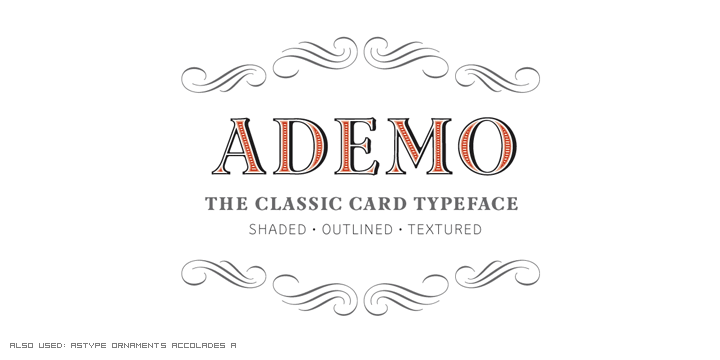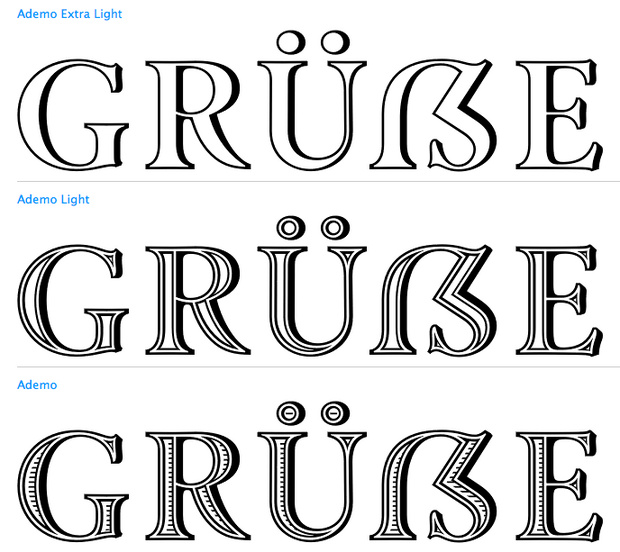
Ademo is a classic, shaded and perspective looking display font. The design is based on two typefaces designed by Carl Albert Fahrenwaldt and published between 1931– 1932 by the German Schriftguss AG type foundry.
Ademos special Fill fonts can be used for building multi colored text or for special finishing needs like blind imaging, embossing, stamping, partial UV coating and laser cutting.
Gilt die Liebesbekundung allein schon der Tatsache daß es ein Versal-ß gibt? Die Form als solches überzeugt mich jetzt nicht wirklich. Wirkt doch ein wenig übergewichtig.
Weil es sich gar so breit macht und damit schreit: »Seht nur her wie wichtig Unsereins ist«?
;-) Das ist doch keine Monospace*schrift – warum sollten die Buchstaben da nicht unterschiedliche Breiten haben? M und W sind doch auch generell breiter (oder wirken optisch breiter) als zum Beispiel L, I oder S – und es tut dem Gesamtbild der Schrift (und ganz allgemein dem aller Schriften) keinen Abbruch. Ich finde es besser, man gibt einem Buchstaben etwas mehr Breite – wenn es der Form des Zeichens gut tut – als wenn man ihn in ein vorgegebenes Breitenraster presst. Die Form des Versal-Eszetts in diesem Fall gefällt mir gut. Der Buchstabe unterscheidet sich ausreichend deutlich vom B, fügt sich dennoch schön in die Formensprache der übrigen Schrift ein und wirkt auf mich nicht wie ein Fremdkörper. :-)
;-) Das ist doch keine Monotypeschrift – warum sollten die Buchstaben da nicht unterschiedliche Breiten haben?
Und was hältst Du vom Versal-Eszett der Ademo?
Es wäre interessant, den Buchstaben mal in anderen in Versalien geschriebenen Wörtern zu sehen. Dann wäre klarer ersichtlich, ob er generell funktioniert oder allgemein etwas zu breit wirkt.
Das sieht wirklich nicht gut aus … viel zu klein, das große.
Hm, wenn ich jetzt noch mal über Ralfs zweites Beispiel schaue: Einen Hauch schmaler könnte es wirklich sein. Na guuut: Ihr habt mich überzeugt. :-D
Was mich hier, wie bei den meisten ESSZETT-Formen, stört, ist der große Weißraum, der links oben entsteht. Die Binnenform finde ich eigentlich ganz okay ...
Und was hältst Du vom Versal-Eszett der Ademo?
Ich komme gar nicht bis dahin, über das Versal-ß nachzudenken, wel ich mir immer sage: Sooo eine schöne Schrift und weit und breit keine denkbare Anwendungsmöglichkeit in Sicht.
Da der Font ja nur Versalien (und small caps, wie ich gerade festgestellt habe) aufweist, bin ich automatisch davon ausgegangen, dass das ẞ durch Eingabe des ß erzeugt wird. Da kommt aber nur das unwesentlich kleinere small-caps-ẞ heraus.
Ich komme gar nicht bis dahin, über das Versal-ß nachzudenken, wel ich mir immer sage: Sooo eine schöne Schrift und weit und breit keine denkbare Anwendungsmöglichkeit in Sicht.
Sooo eine schöne Schrift und weit und breit keine denkbare Anwendungsmöglichkeit in Sicht.
Und ich denk mir: die Schrift naja, aber immerhin breit einsetzbar.
Im Versal-ß statt in die Breite in die Tiefe investiert fänd ich sinnvoller.
Mir gefällt die Schrift eh, ich finde allerdings daß das Versal-ß sich so noch harmonischer einfügt. Ist aber nur meine gänzlich unprofessionelle Meinung. :ilovetype:
Ähnlichkeit mit anderen Buchstaben ist nicht, worauf es ankommt. Breiter ist das SZ dem G und dem O hinsichtlich der Helligkeit ähnlicher, schmaler dem R und dem E. Das ist ein Irrweg. Welche sind die Kriterien? Es gibt durchaus nicht wenige Schriften mit weniger ähnlich breiten Versalien, diese starken Unterschiede sind eine Charaktereigenschaft der Antiqua, der man erst mit Versalausgleich beikommt. Und wie stellt sich das Zeichen in kleineren Graden dar? Läßt es sich ebenso verkleinern wie die anderen, wenn es schmaler gezeichnet ist? Läßt sich das nicht mit einigen Satzversuchen und genauem Versalausgleich in mehreren Graden besser beurteilen als an einem einzigen Wort?
@andreas
Etwas schmaler, so wie von dir neu gestaltet, wirkt im Beispielwort auf mich harmonischer.
In 12 Punkt hat die breitere Version ein etwas besseres Bild. Aber da die Fonts wohl eher größer genutzt werden kann ich mich mit einer schmaleren Version anfreunden.
Danke für das PDF – das ist wirklich hochinteressant. Bei der rein schwarzen Variante der Schrift empfinde ich das breitere Versal-Eszett als stimmiger, denn da wirkt die schmale Version auf mich zu dunkel im Gesamtbild der Schrift. Bei der Outline-Version der Schrift funktioniert das schmalere Versal-Eszett in meinen Augen besser, weil es sich harmonischer zwischen den übrigen Versalien einfügt (mit Ausnahme des 12-Punkt-Schnittes, da stimme ich Dir zu). Danke für diese Einblick! :-)
Gerade bei solchen Designs spielt viel optische Täuschung eine Rolle und Aufgrund der Einheitlichkeit muß man an vielen Stellen einen guten Kompromiß finden.
Die einzelnen Fonts müssen alle Dicktengleich und auch gleich im Kerning sein damit das mit den Layern funktioniert.